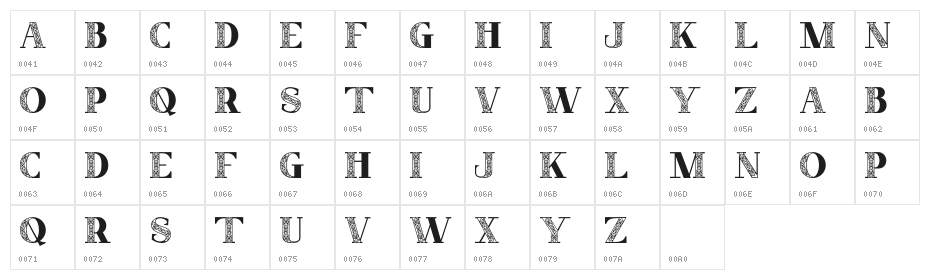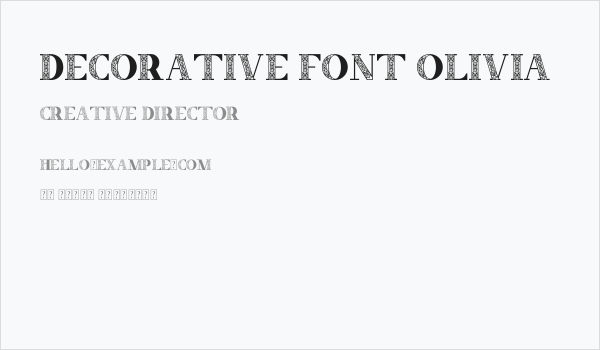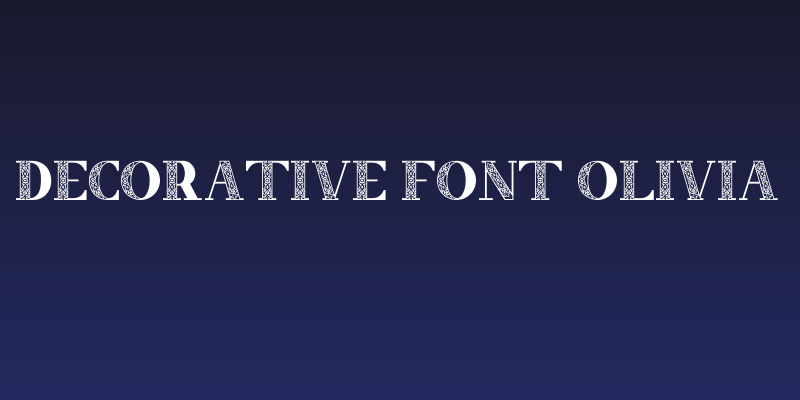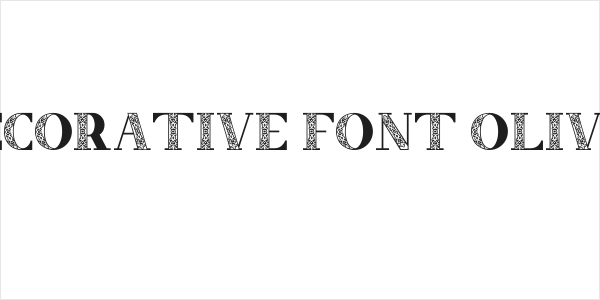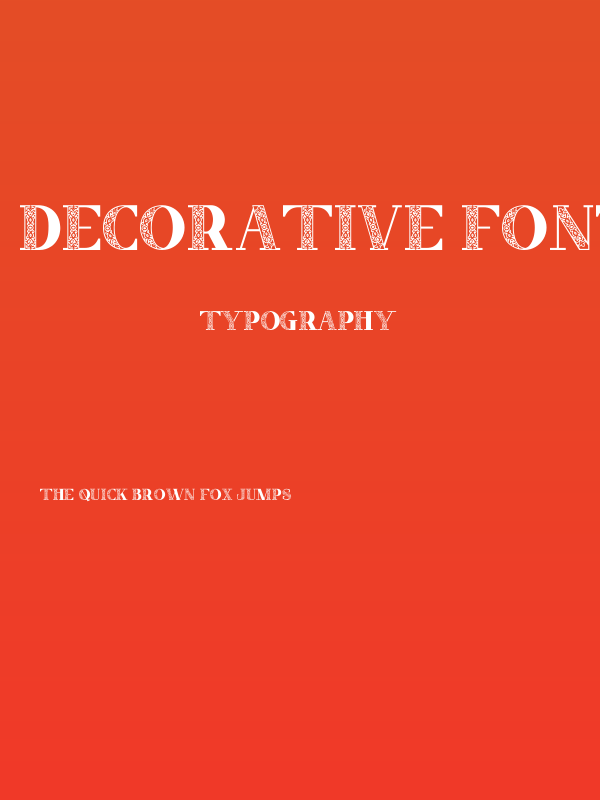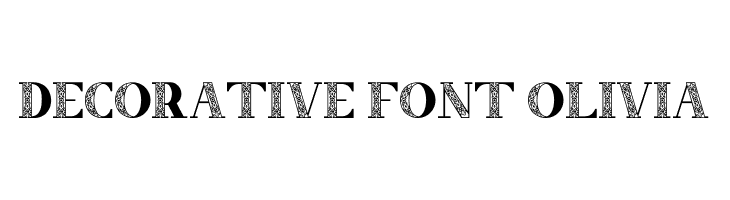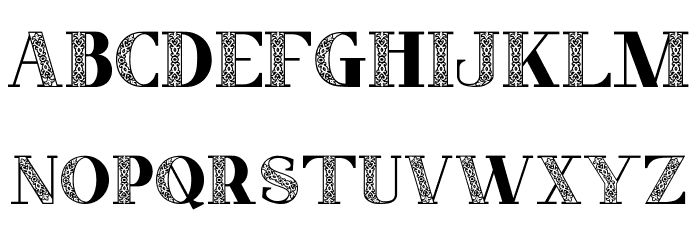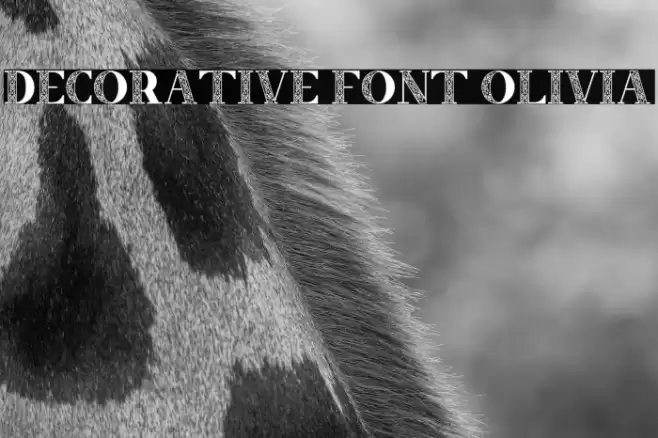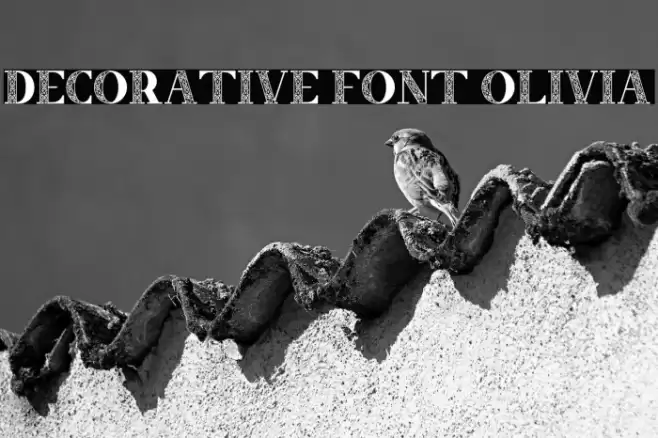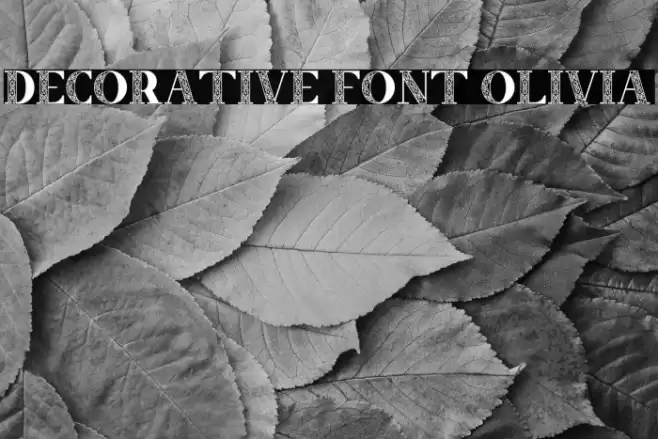
Decorative Font Olivia Font
✎ Serif
| Name | Decorative Font Olivia |
| Schriften Familie | Decorative Font Olivia |
| Style | DecorativeFontOlivia |
| Kategorien | Serif |
| Vorgeschlagene Projekte | Ideal for wedding invitations, luxury branding, artistic posters, and decorative headlines. |